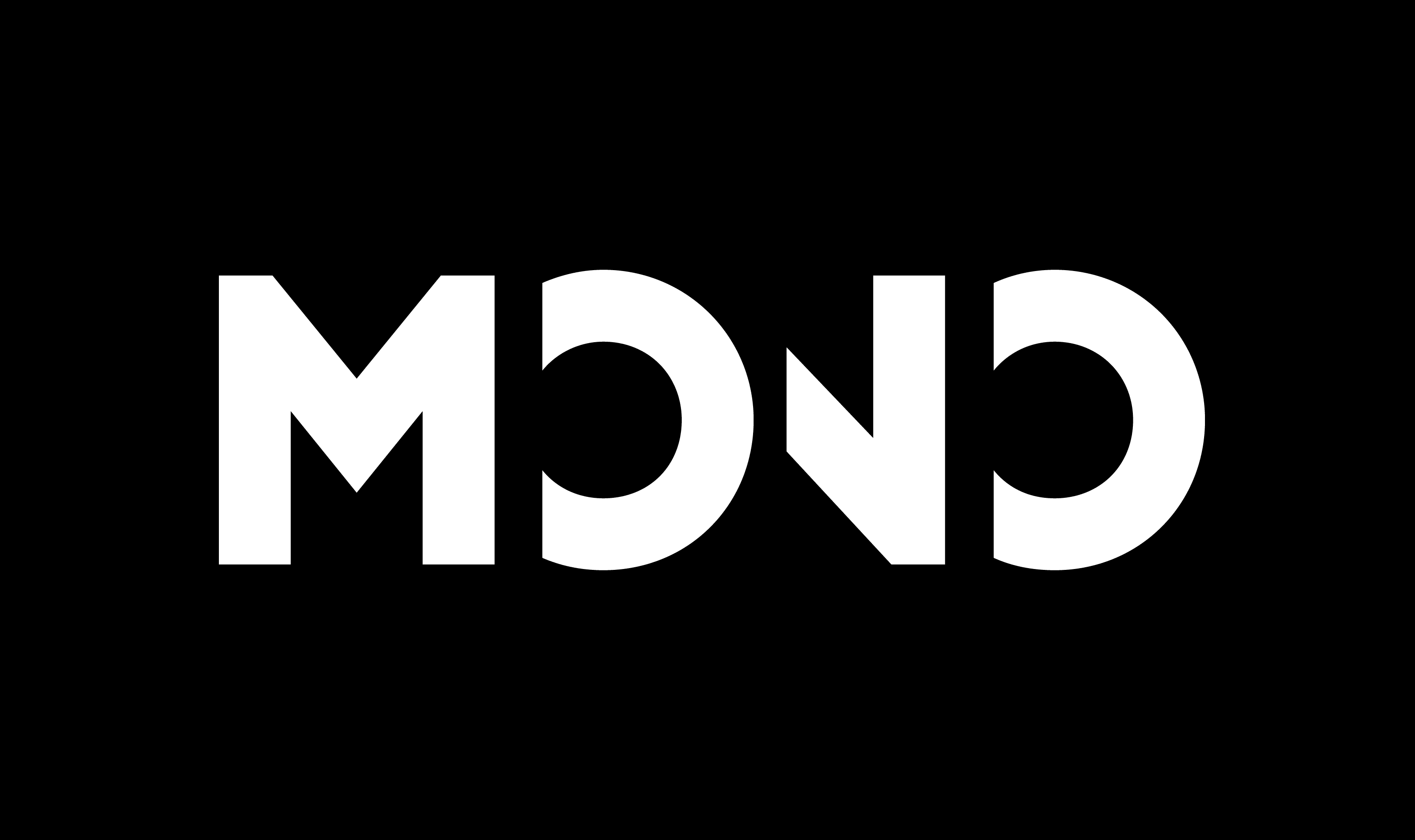
MONO
MONO je mimovládna platforma poskytujúca priestor a podporu inovatívnej žurnalistike na Slovensku. Kladie dôraz na kvalitný obsah a čitateľský zážitok. Hlavným cieľom MONO je otvárať dôležité lokálne témy a prezentovať slovenskému čitateľovi pútavú zahraničnú žurnalistiku.
Jednoduché čiernobiele logo zachytáva myšlienku odkrývania faktov a predstavuje mnohostranné pohľady a názory publikované v online publikácii.